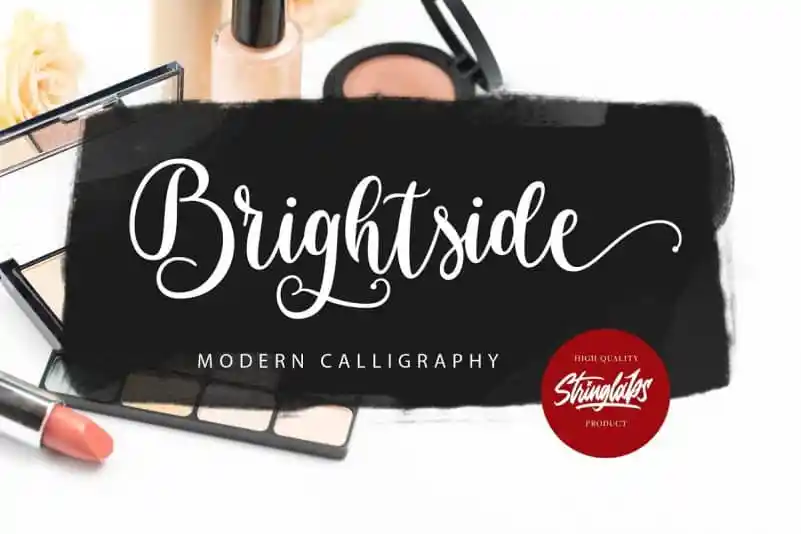
Brightside Calligraphy Font – Download Grátis
A ‘Brightside Calligraphy Font’ é uma opção inovadora para designers apaixonados por letras elegantes. Ela traz um toque moderno e luxuoso às suas criações, transformando qualquer texto simples em um verdadeiro trabalho de arte. Este font script incorpora elementos modernos enquanto mantém a elegância característica da calligrafia. A ‘Brightside Calligraphy Font’ oferece uma variedade de linhas suaves e gérions de alta qualidade com alternativas impressionantes, permitindo ao designer criar texturas interessantes e variadas. Esta font é especialmente indicada para designers que buscam incorporar um toque moderno em seus trabalhos, seja para cartazes de eventos, logos ou até mesmo em design editorial. Com a facilidade PUA encode, todos os elementos do tipo podem ser acessados sem problemas. A ‘Brightside Calligraphy Font’ é definitivamente uma escolha ideal para quem busca um touch elegante e moderno no seu trabalho de design.